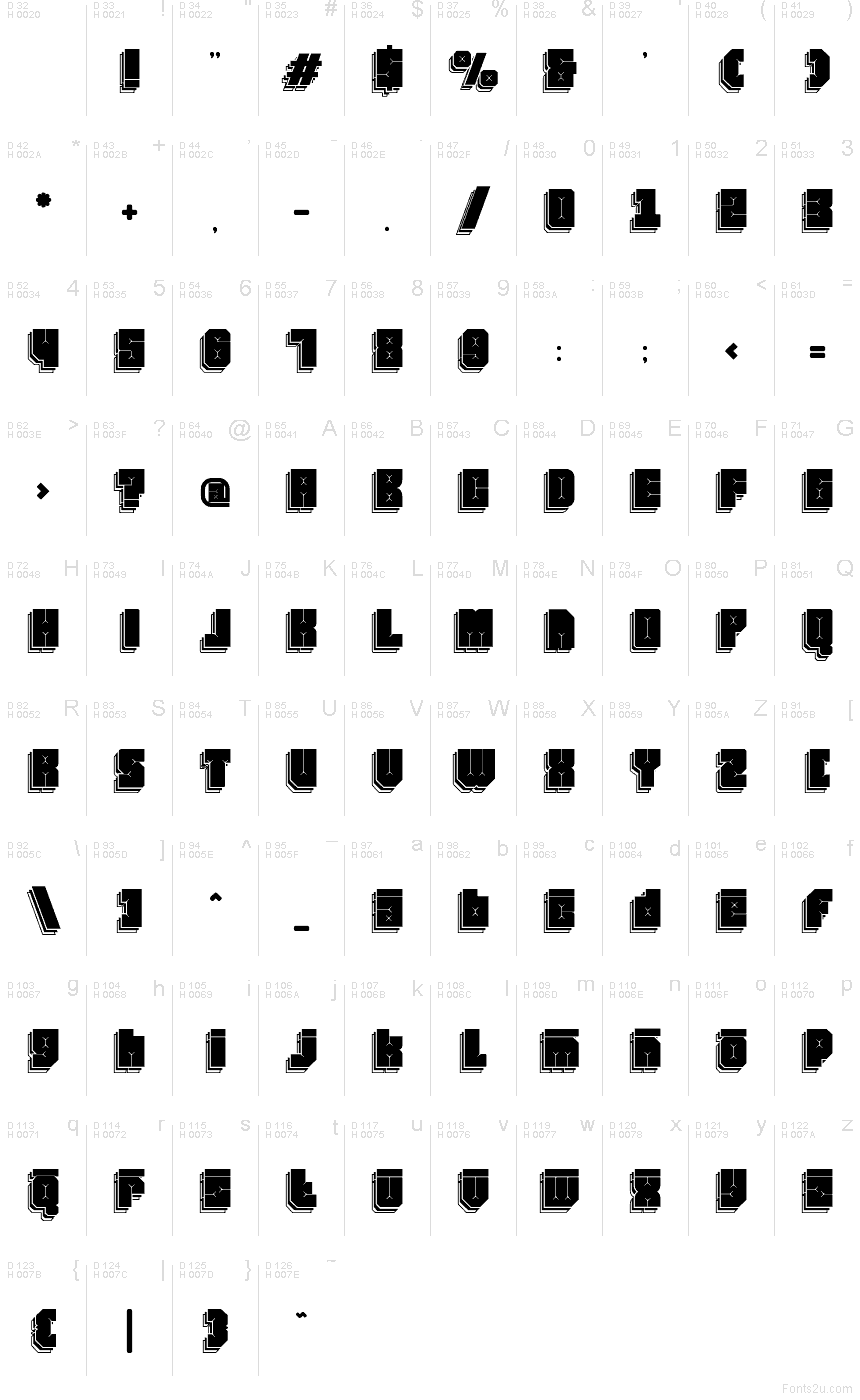
Friez Nine od Putracetol Studio je bezplatné 3D písmo typu display, definované vysokými černými bloky obklopenými odsazenými konturami, které připomínají architektonické výřezy. Tato opakující se struktura dodává písmenům strohý, až labyrintový vzhled, zatímco drobné úhlové vnitřní tahy brání tomu, aby design působil jen jako obyčejný plochý blok.
Plakáty, přebaly alb, titulky akcí, obaly produktů nebo herní grafika – všude tam tato zarámovaná silueta vytvoří silný grafický prvek bez nutnosti dalších efektů. Skvěle vynikne v krátkých logách a nadpisech, kde vrstvený okraj hraje hlavní vizuální roli a úzké vnitřní tahy působí spíše jako znaky vytesané do struktury než jako běžná písmena.
Friez Nine